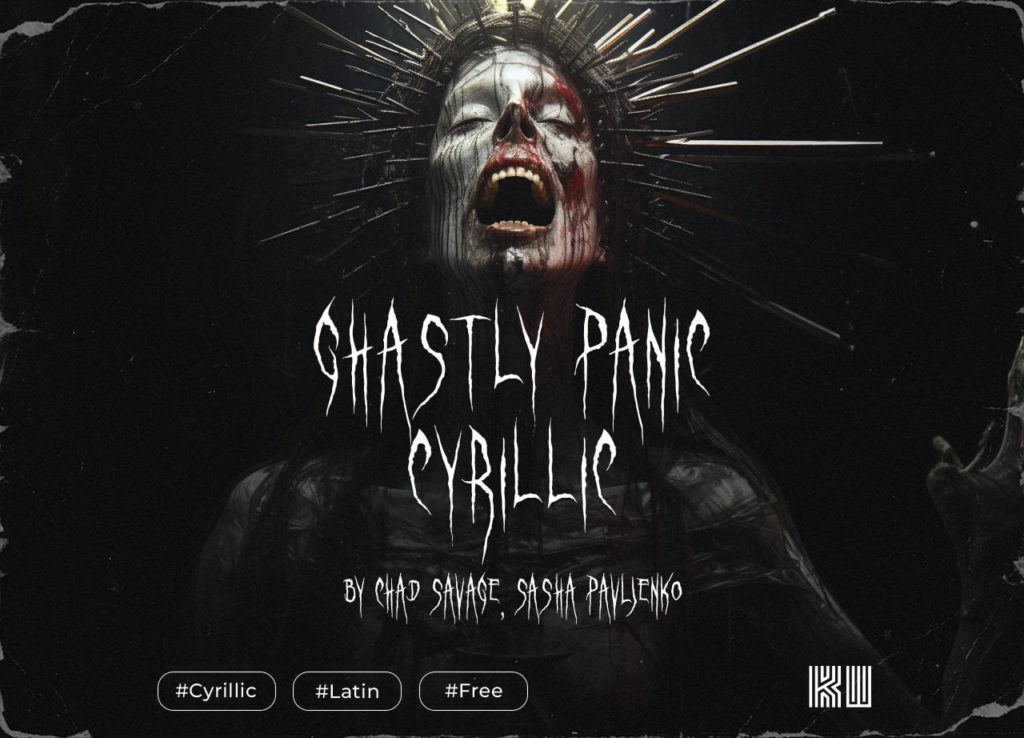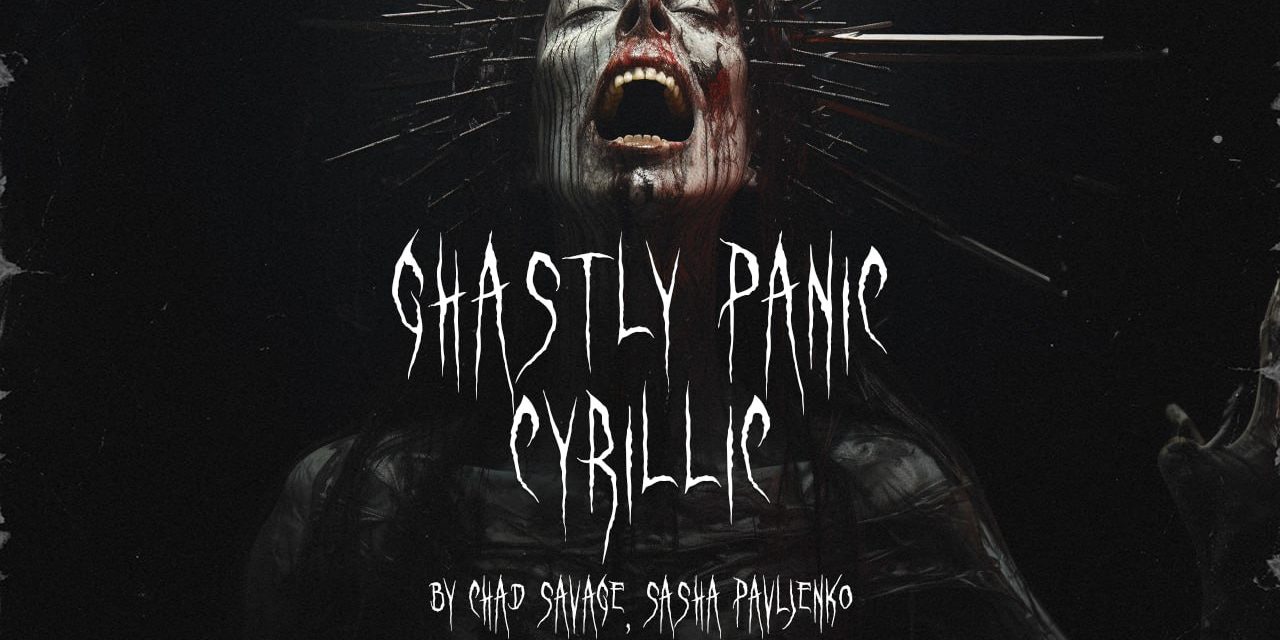
Шрифт Ghastly Panic Cyrillic — это выразительный акцидентный шрифт в стиле хоррор и гранж, созданный для передачи атмосферы ужаса или мрачной готики. Оригинальное начертание (вероятно, инди-дизайнера) имитирует эффект кровавых потеков, рваных краев или старой гравюры, что делает его очень узнаваемым и эмоциональным. Кириллическая версия алфавита была добавлена энтузиастами для расширения возможностей использования в русскоязычном дизайне. Это отличный инструмент для создания пугающих заголовков. Скачать кириллическую версию бесплатно можно по ссылке ниже.